Rotunda
Rundgotische Buchschrift; Hauptschriftgruppe, die gemäß der typografischen Schriftklassifikation zur Schriftgattung der Gebrochenen Schriften gehört. In der Paläografie zählen die kalligraphischen Varianten zu den Hochformen der »Littera textualis formata«; dort auch als »Littera Bononiensis« oder »Halbgotische Schrift« bezeichnet.
Etymologisch leitet sich der Begriff »Rotunda« vom lateinischen »rotundus, -a, -um« für »rund, abgerundet« ab, was so viel bedeutet wie »die Runde, Abgerundete«. Seit dem frühen 13. Jahrhundert ist sie in der Terminologie der Schreibmeister (siehe Kalligrafie) die gerundete Form der gotischen Minuskel.
Als eine Variante der gebrochenen Schriften wurde die Rotunda vorwiegend in Italien, im 14. Jahrhundert besonders in den juristischen Manuskripten der Universität Bologna praktiziert, daher rührt auch ihr Beiname Littera Bononiensis. Nördlich der Alpen, wo (auch) in der Buchtypografie die Textura vorherrschte, wurden physische Rotunda-Drucktypen (Druck-Rotunda) erst ab ungefähr 1485 häufiger verwendet.
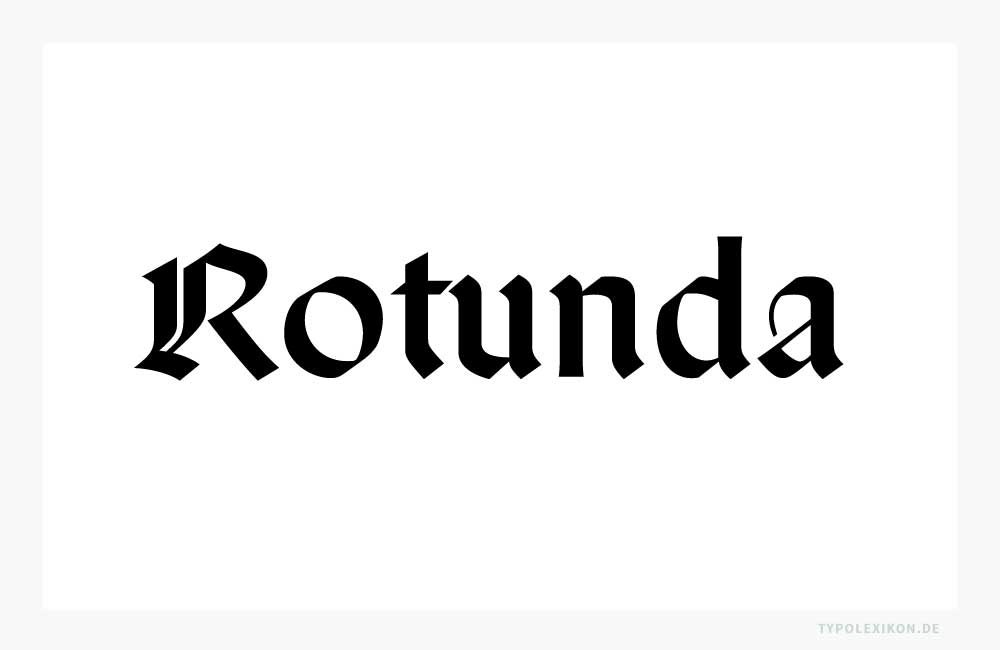
Kalligrafie
Die handschriftliche Rotunda hat ihre Wurzeln unverkennbar in der langobardischen »Beneventana«. So bezeichnet die paläographische Forschung jene auf ganz spezielle Weise bereits »gebrochene« Variante einer präkarolingischen Minuskel, die – ausgehend vom süditalienischen Benediktinerzentrum Montecassino, 1) wo sie seit dem 6. bis ins 12. Jahrhundert in ihrer formstrengen Eigenart kultiviert wurde – die Kalligrafie der monastischen Skriptorien (La Cava, S. Sofia di Benevent, S. Liberatore alla Maiella; Klöster in Capua, Neapel, Salerno und Bari sowie in Calabrien und der Basilicata) entscheidend geprägt hatte.
Zu Beginn des 11. Jahrhunderts drang sie über die Kanzlei der Fürsten von Benevent (Ducato di Benevento, Region Kampanien) auch in den weltlichen Kulturraum zu beiden Seiten der südlichen Adria ein und konnte sich im Buch- wie im Urkundenwesen (siehe Diplomatik) mancherorts bis ins frühe 14. Jahrhundert halten; skriptografische Ausläufer der Beneventana reichten am Ende des 11. Jahrhunderts durch den klosterinternen benediktinischen Literaturtransfer sogar bis nach Nordfrankreich (Mont Saint Michel) und verdrängten von dort her als »Carolino-Gotica« genannte Mischform zunehmend die runde »Karlingische Minuskel«. Die authentische »Gotische Minuskel« konnte sich erst im Verlauf des 13. Jahrhunderts durchsetzen.
Charakteristisch für die vollendet kalligrafierte Beneventana sind die gleichmäßige Deutlichkeit ihrer Zeichen und das Ebenmaß des Schriftbildes. Eine ganz bestimmte Haltung des schräg zugeschnittenen Federkiels, verbunden mit einer sorgfältigen Verteilung des Drucks, bewirkte die gebrochene Form der Buchstabenschäfte von i, m, n, u, h und t und die eckigen Linien der Bogenbestandteile von a, b, c, d, e, f, g, p, q, s und t. Die Langstriche zeigen an ihrem oberen Ansatz eine typische Verdickung; die Minuskel a wird seit dem 10. Jahrhundert immer durch die geschlossene, oben leicht eingekerbte cc-Form dargestellt, das o ähnelt einer weitdimensionierten Raute. Manuskripte in der Schrift von Montecassino und Benevent weisen ganz eigenartige, sonderbare Initialen auf, die aus phantastischen Fabelwesen, geometrischen Figuren und kompliziert verschlungenen Bändern bestehen. Signifikant sind auch die Abbreviaturen und Ligaturen, besonders aber die neuartige Bogenverbindung, mit der Buchstaben, die mit einer Rundung enden, in den folgenden rund beginnenden Buchstaben hineingeschrieben werden.
Hauptcharakteristikum der skriptographischen Hochform der altitalienischen Rotunda im 13. und 14. Jahrhundert ist neben den betonten vertikalen Grundstrichen vor allem ihr breiter Duktus. Die zeitgemäß gotischen Brechungen der Rundteile der Buchstaben sind sichtbar gemildert, die zarten An- und Abstriche hingegen fehlen fast völlig. Typisch für eine Rotunda ist der zweistöckig ausgebildete Buchstabe a, mit einer auffallend kleinen unteren Schlinge und einem hochgezogenen Hals, der mit einem Haarstrich nach links umgebogen wird und zumeist so tief hinunter reicht, daß der Kopf völlig geschlossen wirkt. Signifikant ist auch die trapezartige Weitung der unteren, ebenfalls geschlossenen g-Schlinge.
Typografie
Die schon in den benediktinischen Skriptorien jahrhundertelang gepflegte rundgotische Schrifttradition wirkte natürlich auch stilbildend in den Anfängen des italienischen Buchdrucks fort. Neben der aus der Humanistenhandschrift generierten, weltlich-intellektuellen Antiqua für den Druck der antiken Klassiker und Humanistentexte konnte sich die »klerikale« Rotunda vor allem für biblische, liturgische und kirchenrechtliche Literatur zumindest bis 1500 durchaus behaupten.
Während Arnold Pannartz (o.A.–um 1476) und Conrad Sweynheym (o.A.–um 1474/1477), die deutschstämmigen Prototypografen Italiens, im Kloster von Subiaco bereits mit den Prototypen einer (noch gotisch anmutenden) Antiqua experimentierten, druckte der Ingolstädter Prototypograf Ulrich Han (um 1425–nach 1478) in Rom 1466 die »Meditationes« des spanischen Theologen Johannes de Turrecremata (Juan de Torquemada, um 1388–1468) mit einer großformatigen Rotunda, die in Schnitt und Dimension die zeitübliche Schreibschrift wiedergibt. Der Unterschied zwischen zarten Haar- und dunklen Schattenstrichen ist vor allem bei den Minuskeln a, e, u und n recht deutlich ausgeprägt, die Schäfte der Oberlängen sind mit ganz kleinen Ansatzstrichen verziert. Die Majuskeln hingegen sind fast völlig schmucklos und ohne jede Verschnörkelung. Charakteristisch für die Rotunda von Han ist das i mit und ohne Punkt respektive Strich und mit verschieden geschnittenem Schaft. Die beiden frühesten Ausgaben (21. April 1475 und 12. Oktober 1476) des Missale Romanum (Hauptbuch der katholischen Liturgie) setzte Ulrich Han in zwei Schriftgraden der Rotunda.
Zum Zentrum der italienischen Druckrotunda wurde Venedig. Vor allem in der Offizin der deutschen Gebrüder Johannes (o.A.–1469/1470) und Wendelin (o.A.–1477) von Speyer (Giovanni and Vendelino da Spira) entwickelte sich die rundgotische Schrift zu einer ersten Hochform. Für juristische Werke schuf Wendelin de Spira (o.A.) 1470 eine später weitverbreitete mittelgroße Textschrift, die jener des Ulrich Han in Rom wohl ähnlich war, aber Verzierungen an fast allen Majuskeln, parallele Diagonalstriche in deren Rundungen und zumeist auch verdoppelte Schäfte aufweist; bemerkenswert an de Spiras Typen ist vor allem das große Ebenmaß der Minuskeln.
Ihre ausdrucksvollste Blüte verdankt die Rotunda – wie auch die Antiqua – jedoch dem französischen Typografen und Graveur Nicolas Jenson (um 1420–1480), der nach seinen Mainzer Lehrjahren zunächst für Johannes von Speyer (o.A.–1469/1470) – infolge für seinen Bruder Wendelin (o.A.–1477) – als Werkmeister arbeitete und sich 1475 selbständig gemacht hatte. Jensons rundgotische Lettern, die bald europaweit als Vorbild für neue Rotundatraditionen dienten, sind von klarer Einfachheit und geradezu puristischer Schönheit, meist unverziert, breit, aber mit betonter Vertikale, und selbst in kleinsten Schriftgraden deutlich lesbar.